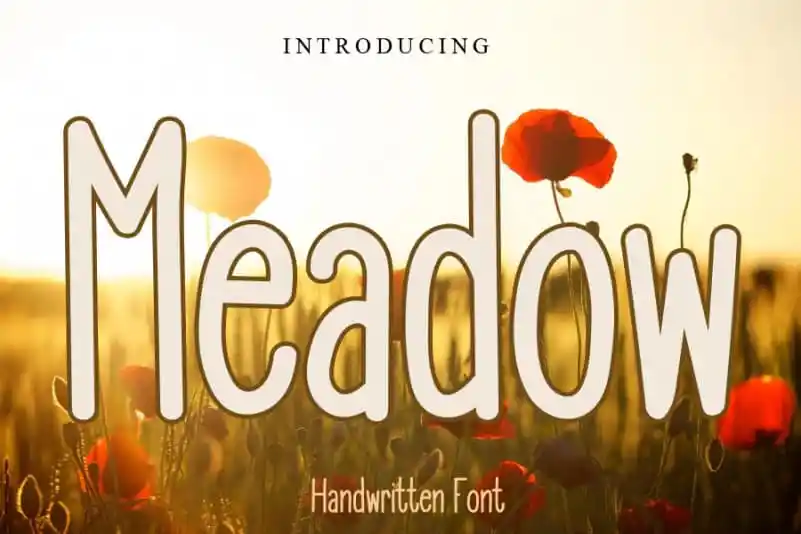
Meadow Display Font – Download Grátis
Meadow Display Font é uma elegante fonte escrita à mão, suave e agradável ao olho. Inspirada na natureza do desenho humano, ela traz um toque único e natural que torna-a perfeita para diversas aplicações gráficas. Seu estilo distingue-se dos demais com uma personalidade rica e única, limitado apenas pelo seu imaginativo uso. Esta fonte é adequada a muitas categorias de design, desde logotipos e selos até layouts de websites e publicações impressas. Suas linhas delicadas e desenhos fluidos permitem que você crie elementos gráficos semelhantes à escrita em um caderno, tornando-a perfeita para designers que valorizam uma aparição natural e familiar. A Meadow Display Font é a escolha ideal se você está buscando um estilo de fonte casual mas altamente profissional. Suas características não só permitem o uso tradicional de texto, como também oferecem a capacidade de criar efeitos interessantes, tornando-a uma ótima opção para designers que buscam algo diferenciado no seu próximo projeto. Meadow Display Font é uma fonte que se encaixa perfeitamente na categoria de Script Fonts, projetada para designer de nível avançado ou iniciante. A natureza única e suave dessa fonte a torna um recurso gráfico indispensável para quem procura algo que não seja apenas uma fonte simples.